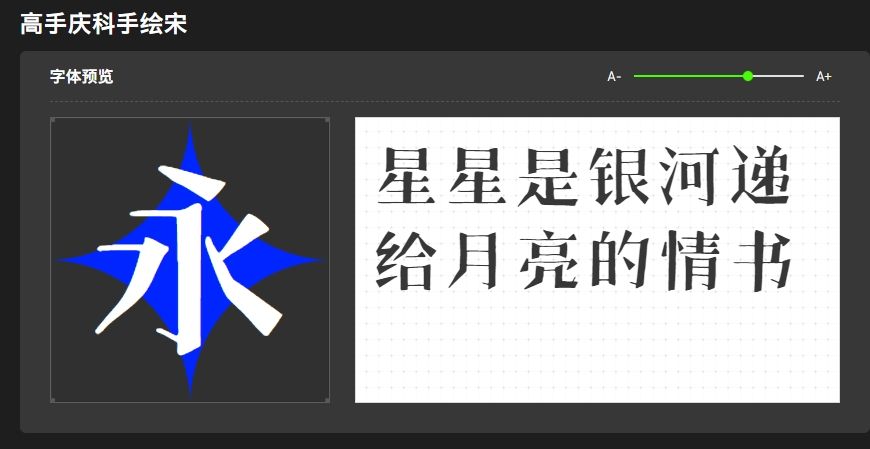
清新自然的宋体字体,为设计增添一份雅致!
在浩瀚的字体海洋中,宋体以其独特的魅力,赢得了无数设计师的青睐。它的线条流畅、结构均衡,犹如一幅幅精美的水墨画,将文字与艺术的结合展现得淋漓尽致。
宋体字体在设计中常常被用于需要展现雅致、清新风格的场合。无论是海报设计、书籍排版还是网页设计,宋体都能为作品增添一份独特的韵味。它的笔画起伏有致,既有力度又不失柔美,仿佛能引领读者进入一个宁静而美好的世界。
高手庆科手绘宋,该字体是一款手写感为基础的宋体,字体设计生动灵活。笔画设计保持传统宋横细竖粗的特点,曲线硬朗。横笔画末端加入三角形装饰角,长撇笔画加入转折,与传统宋体撇笔画形成强烈对比,钩笔画笔形细长,略微上挑,具备更强的趣味性的视觉效果。
此外,宋体字体还具有良好的可读性和辨识度。即使在较小的字号下,也能保持清晰易读的特性,这对于需要长时间阅读的文本来说尤为重要。
因此,如果你正在寻找一款既能展现雅致风格又具有实用性的字体,那么宋体无疑是一个不错的选择。